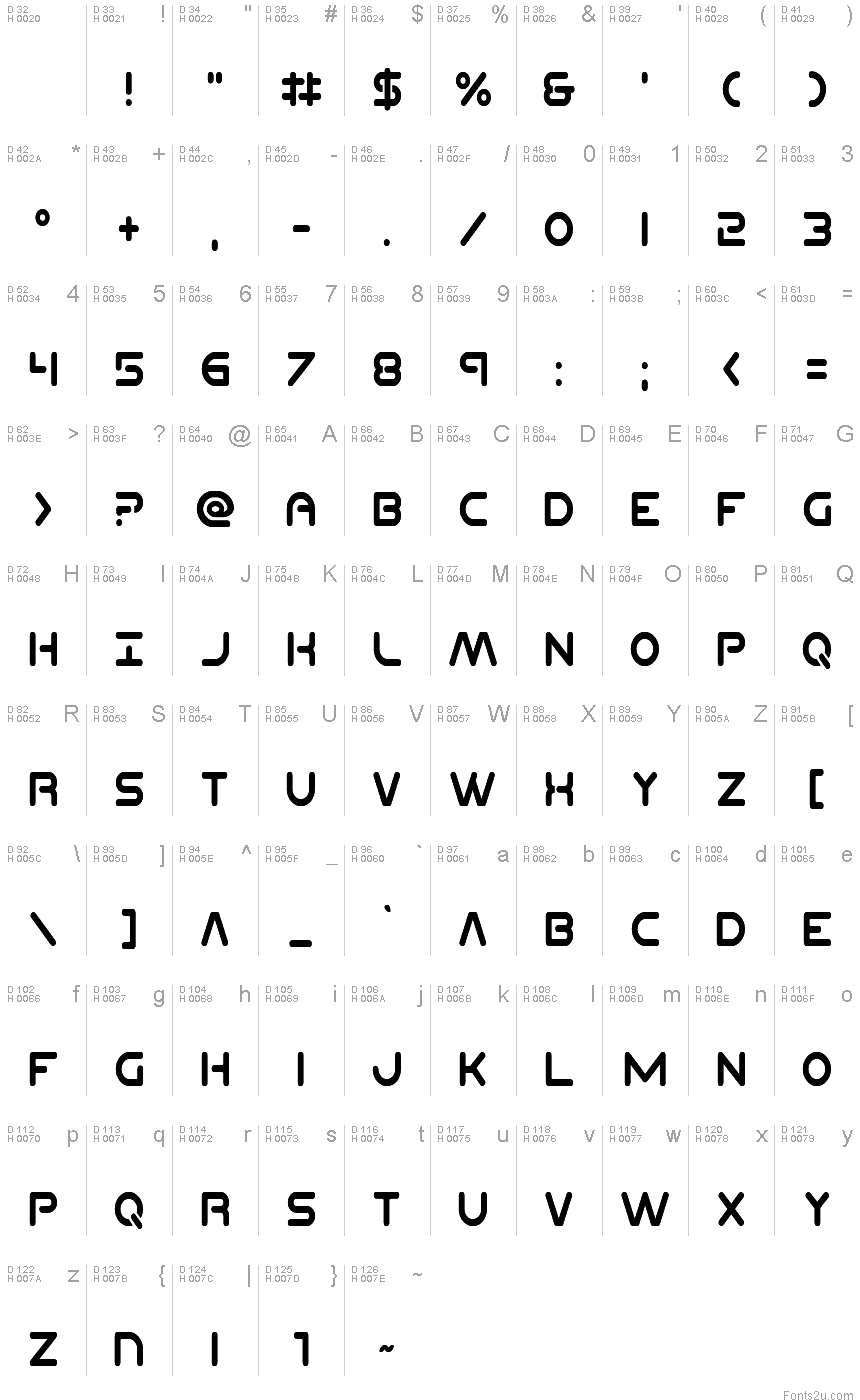
خط Planet N Condensed من Iconian Fonts هو خط عرض (display) مستقبلي ومجاني بأحرف كبيرة فقط، يضفي لمسة خيال علمي نقية. تمزج الحروف بين الزوايا المستديرة الناعمة والقطع الحاد، مما يمنح الأبجدية طابعاً انسيابياً وميكانيكياً في آن واحد، مع أشكال مبسطة تميل نحو التصاميم الإرشادية، والواجهات الرقمية، ورسومات الفضاء ذات الطابع القديم.
هذا يجعل من هذا الخط المجاني خياراً طبيعياً لشعارات الألعاب، وعناوين الملصقات، وأغلفة الموسيقى، والعلامات التجارية التقنية، وبطاقات العناوين حيث تحتاج الكلمات القصيرة إلى مزاج اصطناعي ومضبوط. كما يعمل بشكل جيد للمونوجرامات وعناوين الأقسام، لأن الأشكال المختزلة تحافظ على مظهر جريء ورسومي دون أن يبدو صاخباً.